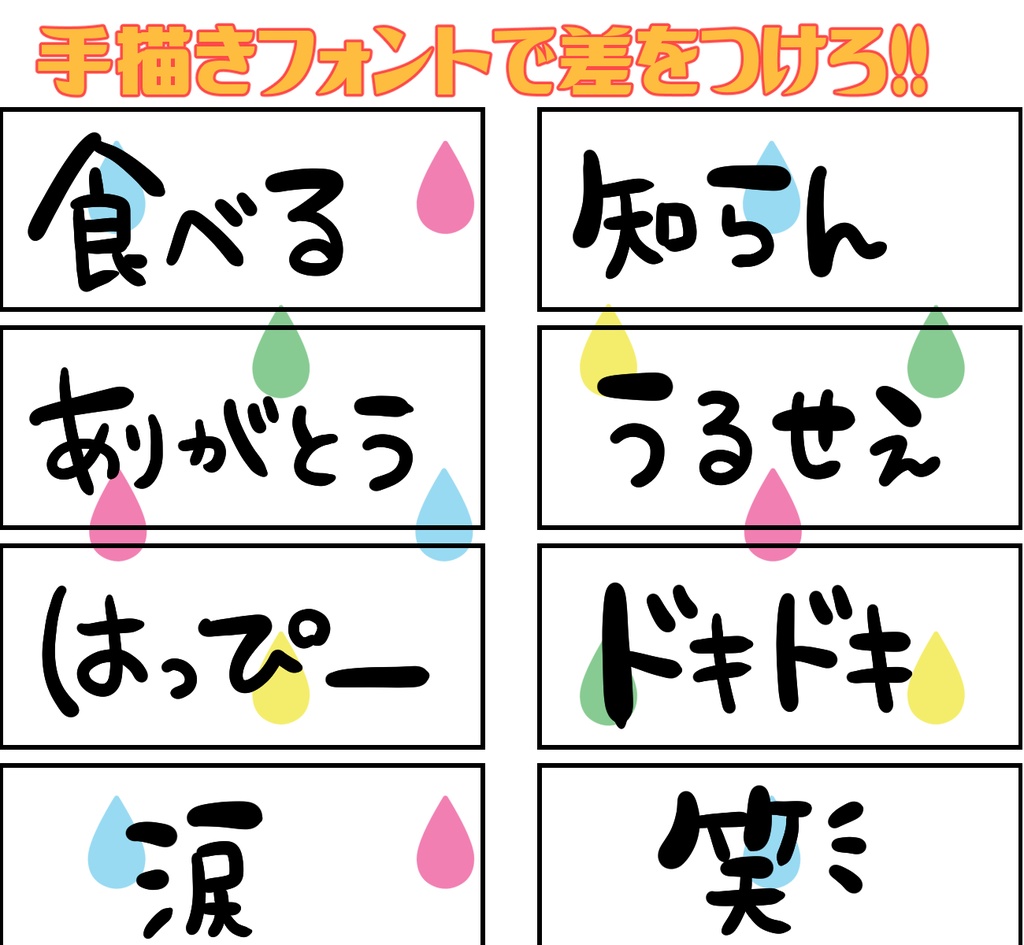
akiramoko手書きフォント・文字素材詰め合わせ応援パック(内容は同じです)Digital100 JPYAdd to CartBuy a GiftダウンロードDigital0 JPYFree Download3.png (119 KB)Free Download2.png (123 KB)Free Download4.png (102 KB)Free Download1.png (137 KB)3.png2.png4.png1.pngAbout Gift柔らかな印象の手描きフォントです。 サムネイルや配布物、動画内素材 こちらは配信者向けのワードが多いかと思います。 様々な用途でお使いになれます。 PNGデータ 黒字ですが、色変更拡大縮小変形、ご自由にお使いください。 ※自作発言ご遠慮くださいakiramokoVisit FANBOX!Acrylic Keychains素直な猫のアクキーakiramoko880 JPYStickersサーモンしか食いたくないステッカーakiramoko450 JPYT-Shirtsサーモンしか食いたくない人用Tシャツakiramoko1,900 JPYWallpapers素直な猫の壁紙akiramoko100 JPYAcrylic Keychains素直な猫akiramoko1,060 JPYAcrylic Keychains騒がしい素直な猫akiramoko1,060 JPYAcrylic Keychains嘔吐ネコakiramoko750 JPYStickers騒がしい素直な猫のステッカーakiramoko770 JPYStickers素直な猫のステッカーakiramoko770 JPYT-Shirtsやるなら今しかねぇ猫akiramoko1,750 JPYIllustration (Other)歯科衛生士・イラスト詰め合わせakiramoko100 JPYGlasses & Tumblers & Mugsクロネコマグakiramoko1,750 JPYAcrylic Keychainsクロネコチャンakiramoko880 JPYIllustration (Other)手書き文字・文字素材詰め合わせakiramoko100 JPYFonts手書きフォント・文字素材詰め合わせakiramoko100 JPYBackground Images背景画像・星空akiramoko0 JPYSee More